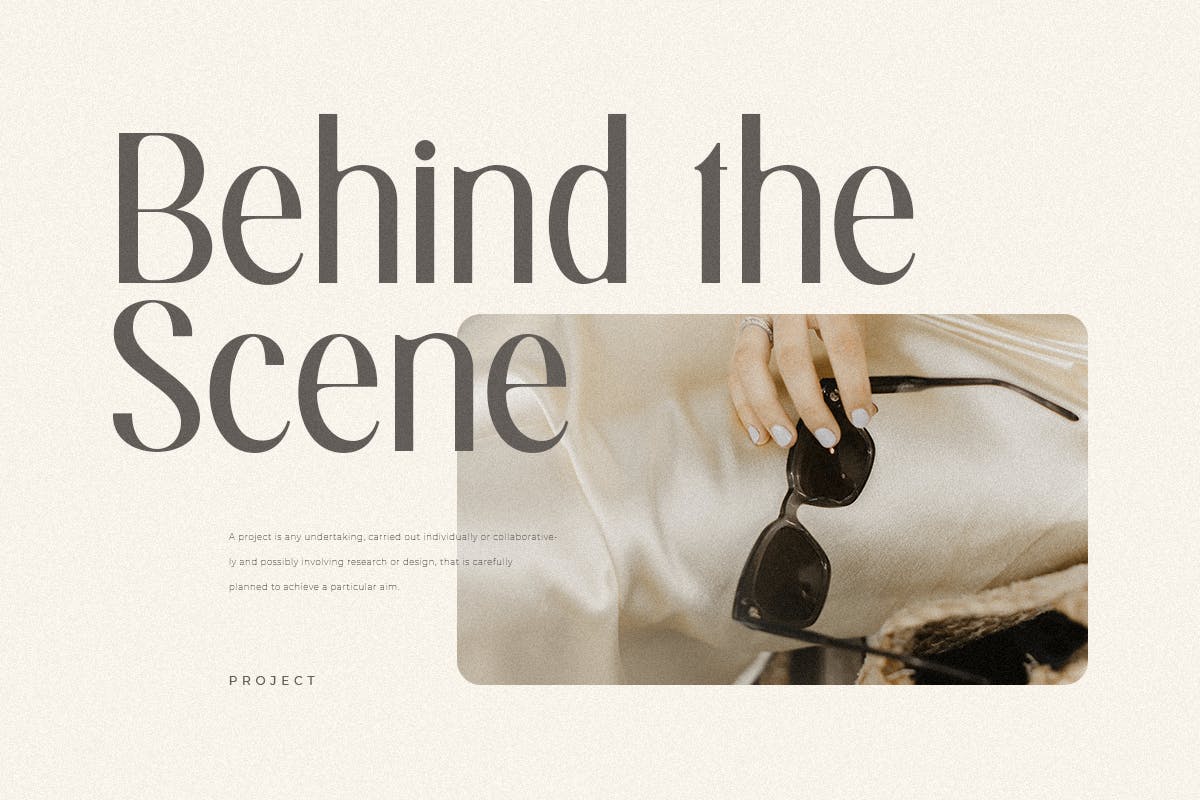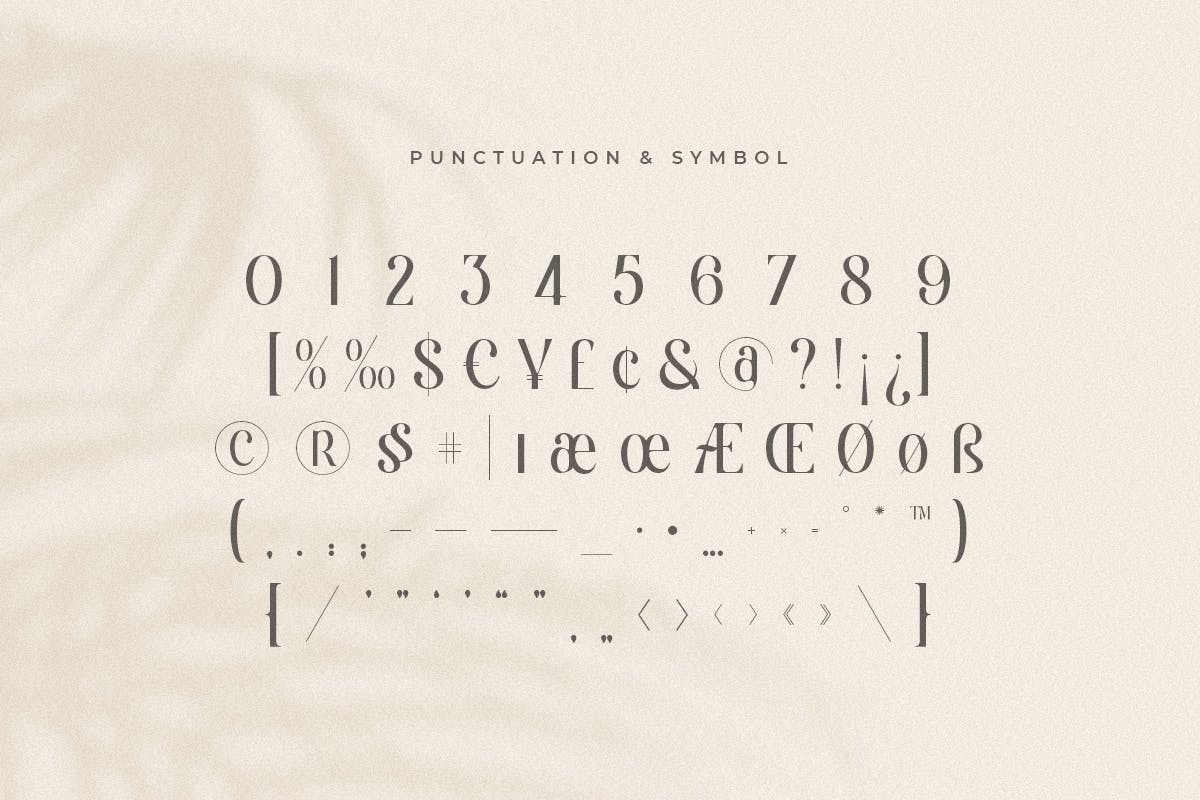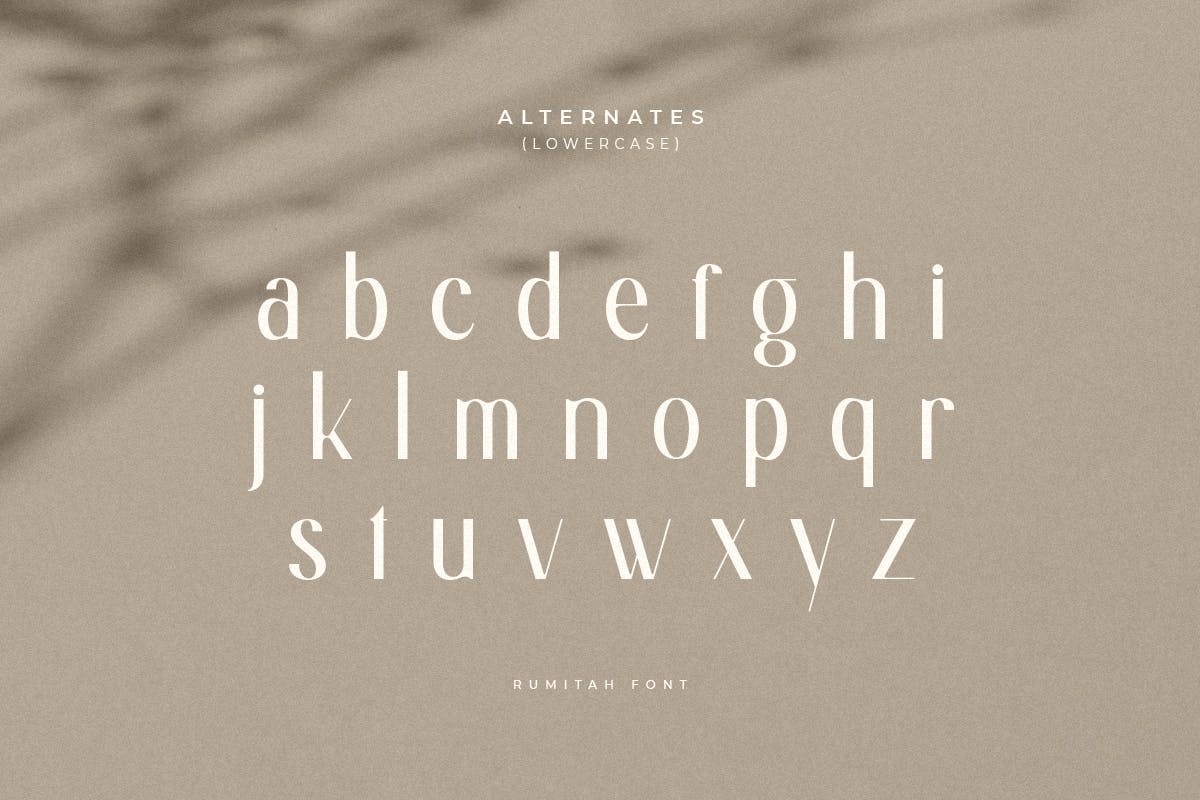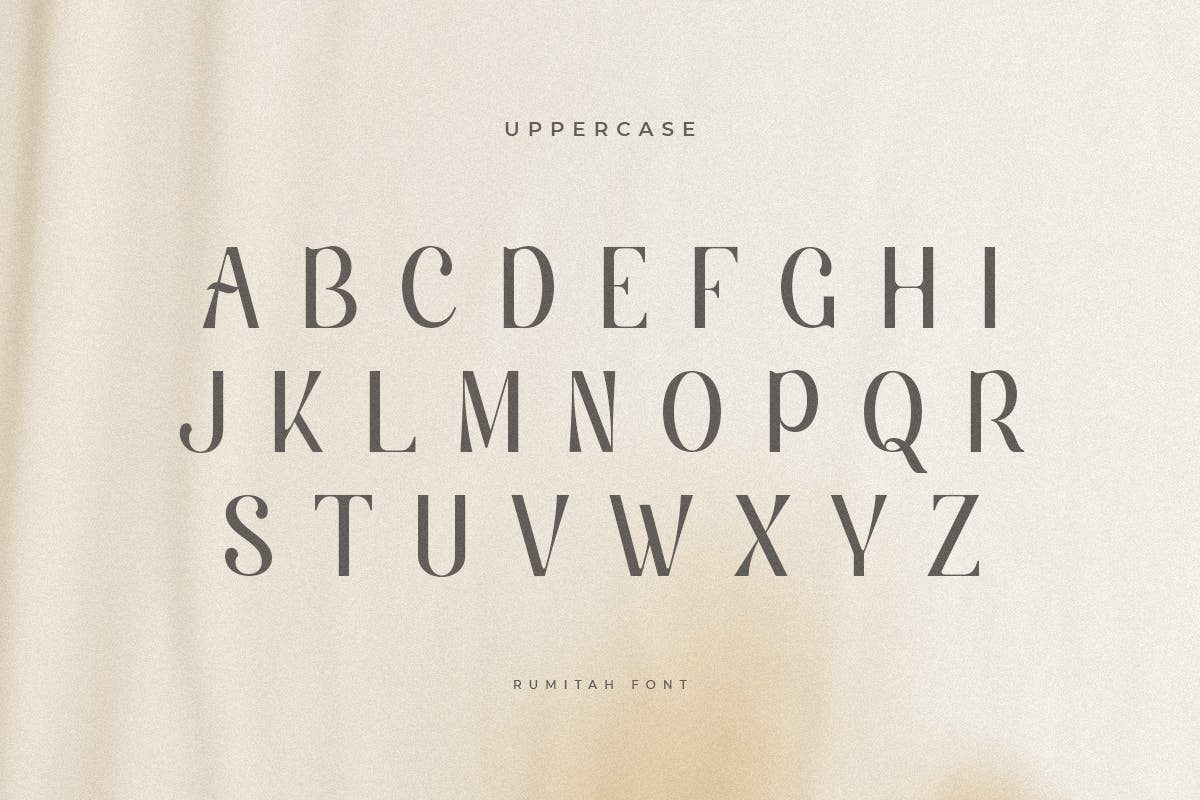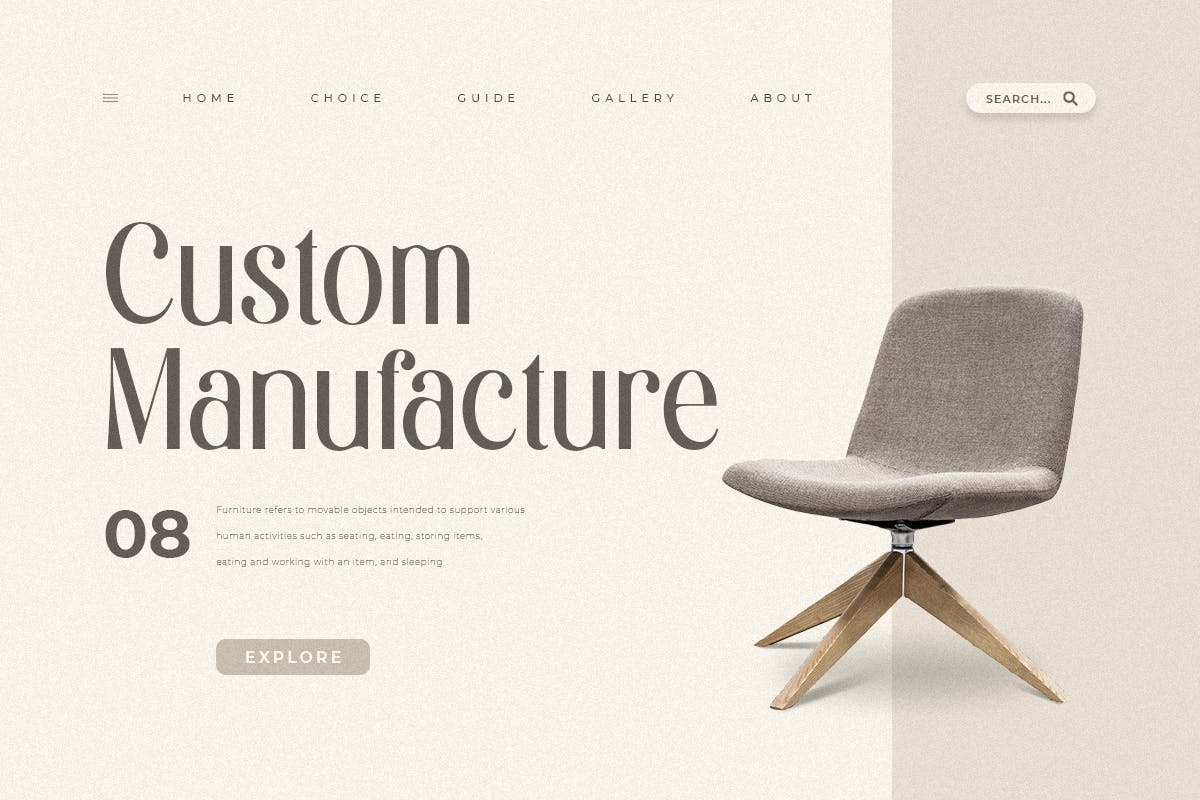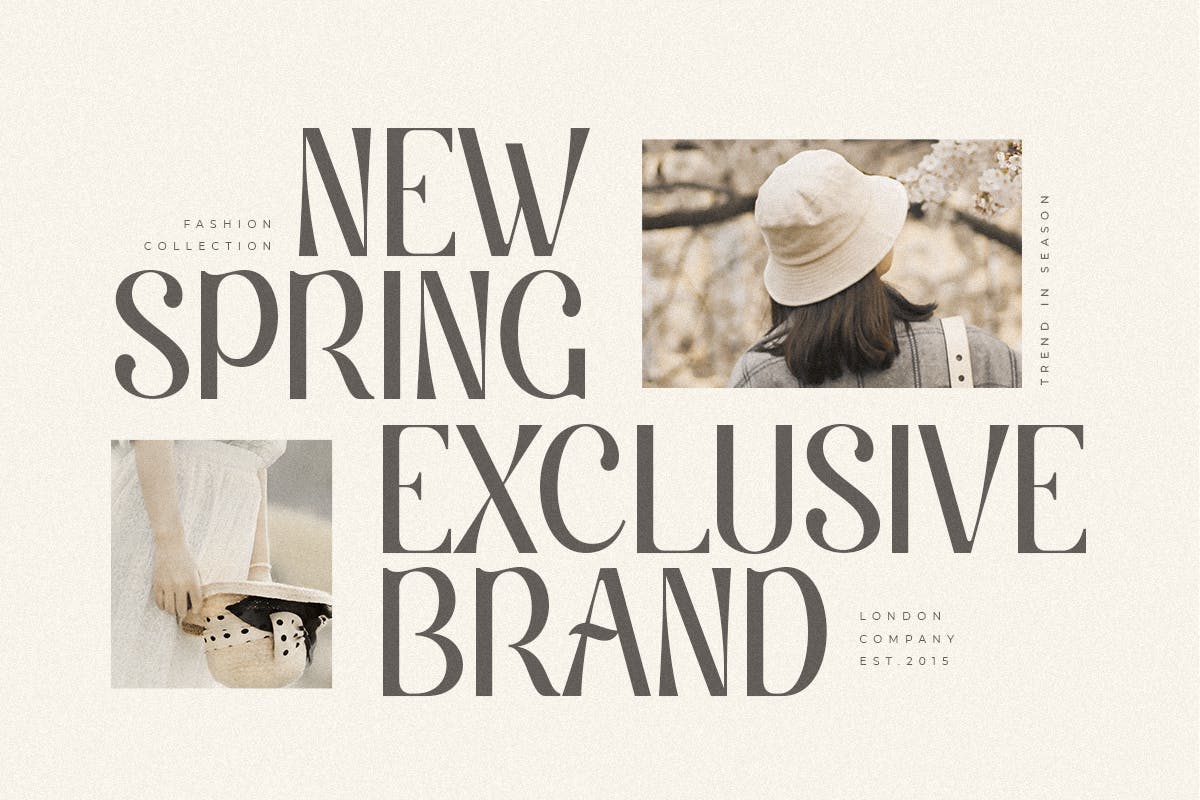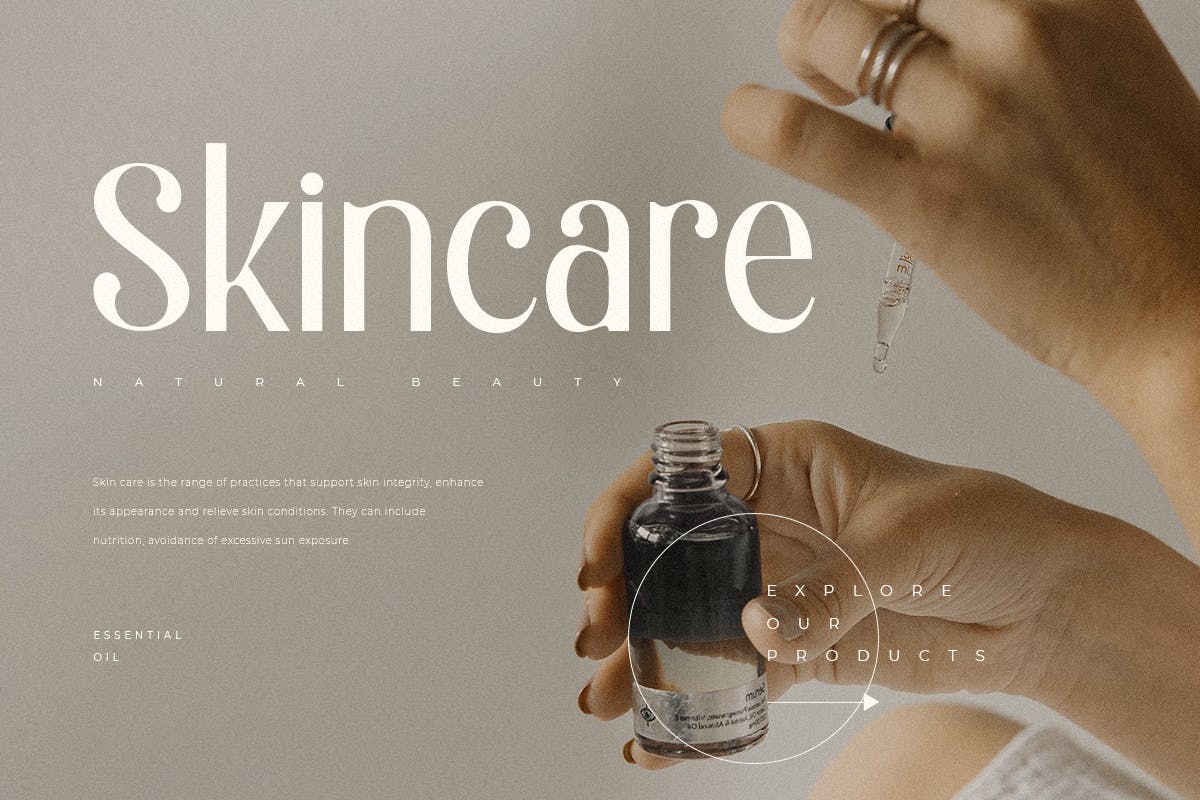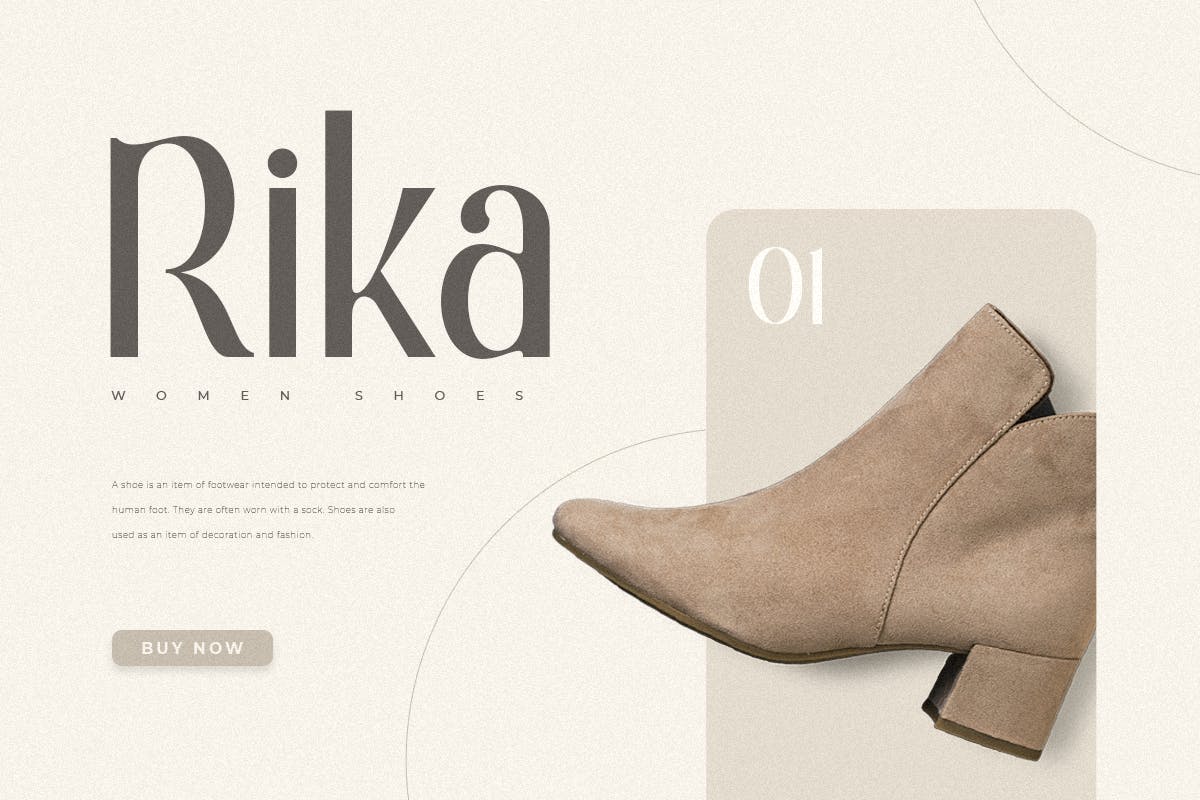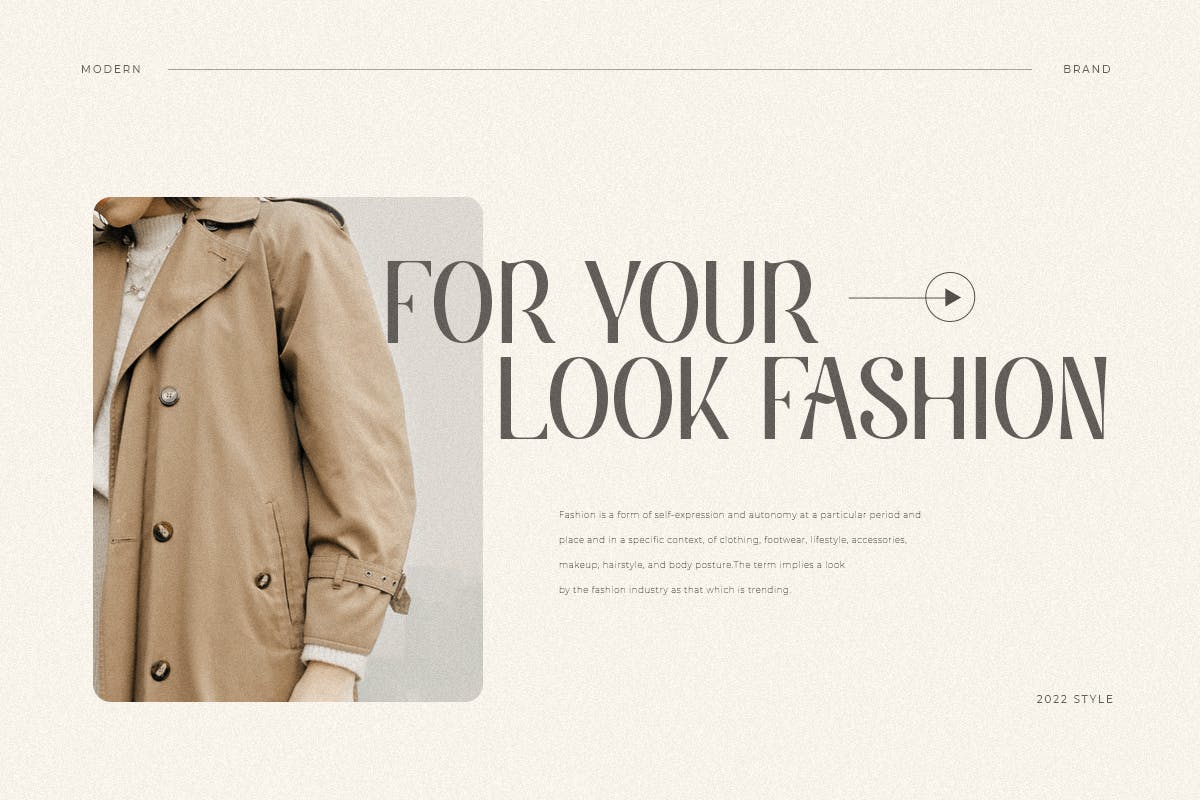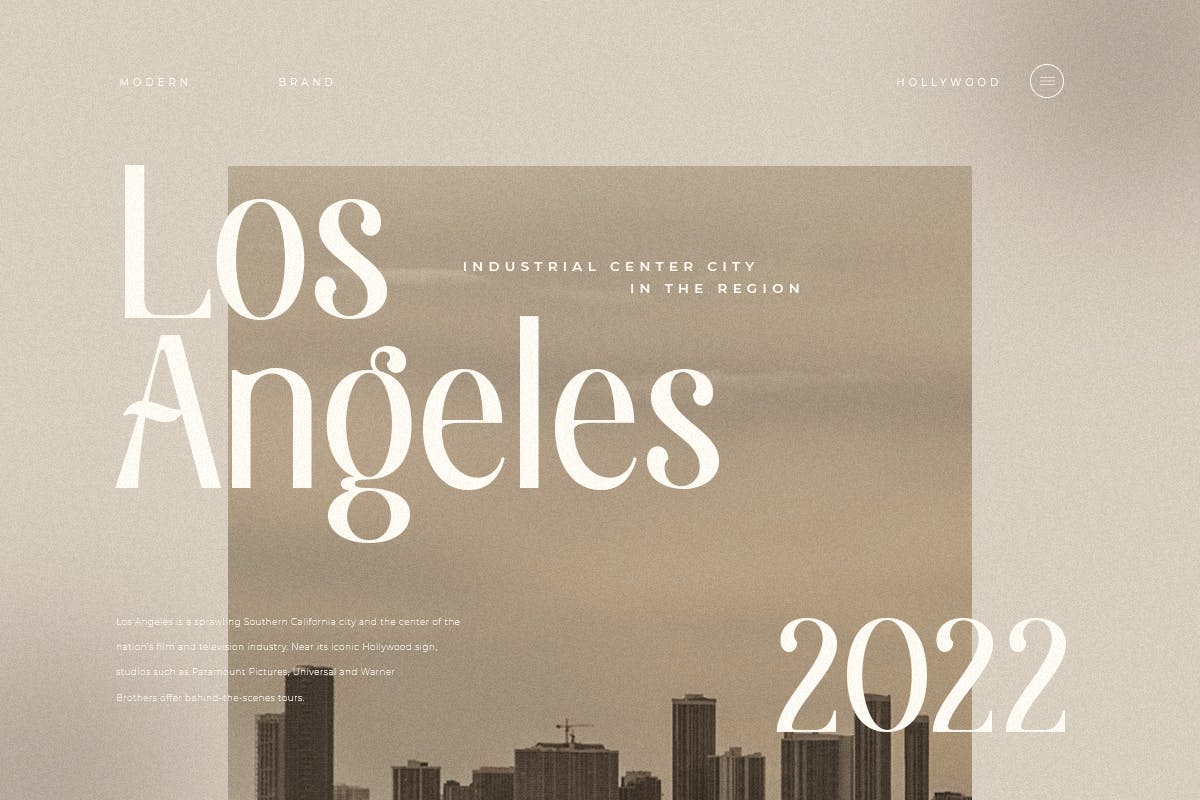
فونت رومیتاه یک فونت مدرن و لوکس با طراحی خاص است که برای نمایش عناوین و لوگوها با سبک شیک و منحصر به فرد آماده شده است. این فونت با شکلهای خاص خود به شما کمک میکند تا ارزش برند خود را افزایش دهید. این گزینه عالی برای طراحان و مالکان محصولات است که به دنبال راهحلهایی برای زیباتر کردن طراحیهای خود هستند. بهویژه برای فونت رومیتاه، ما کاراکترهای متنوعی را آماده کردهایم تا به شما در ایجاد واریانتهای نامحدود برای نیازهای خلاقانهتان کمک کنیم.